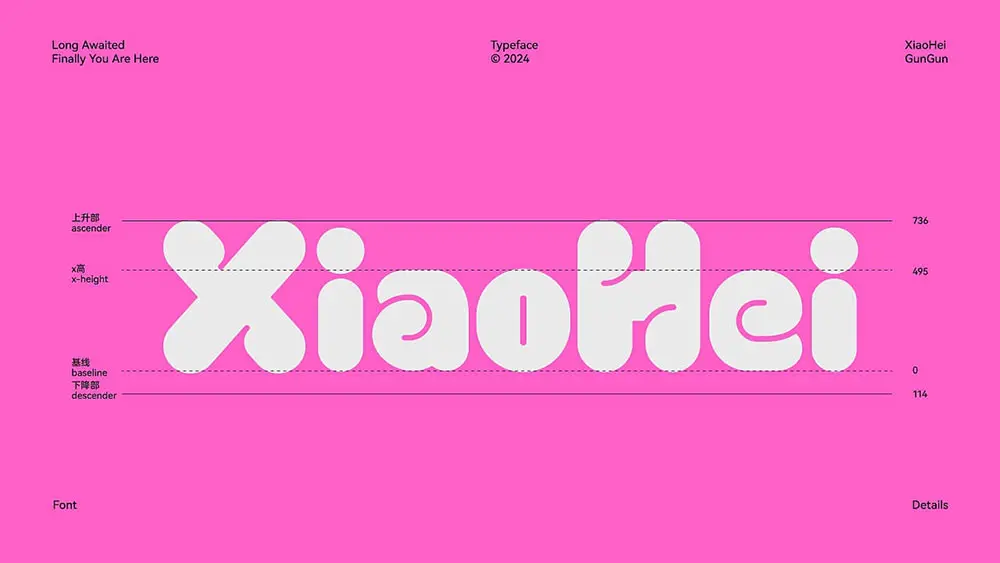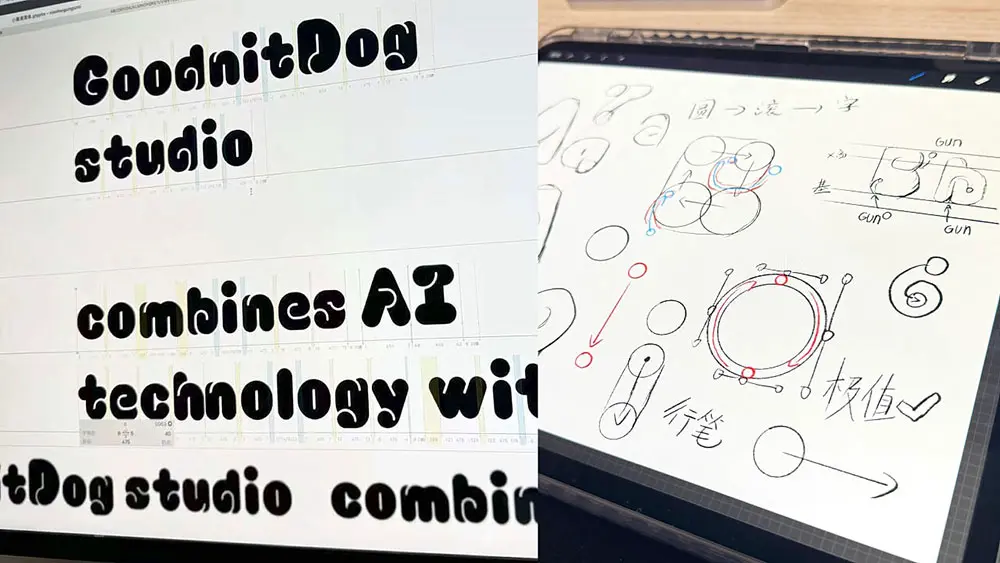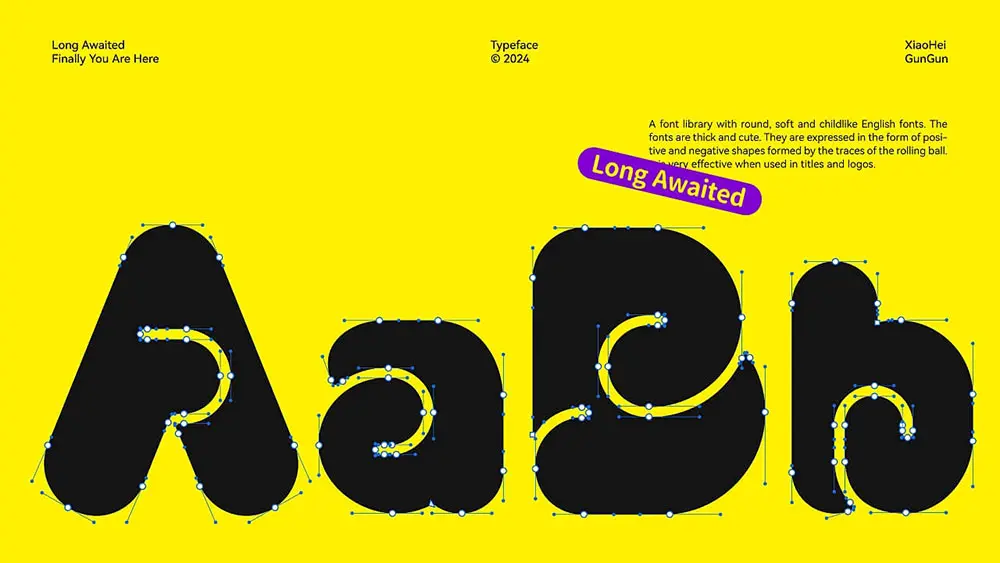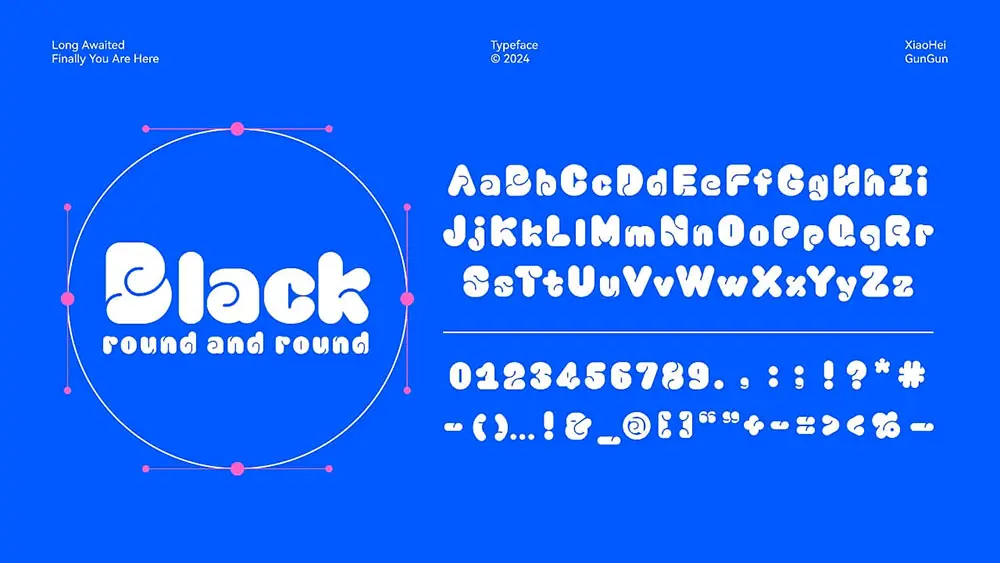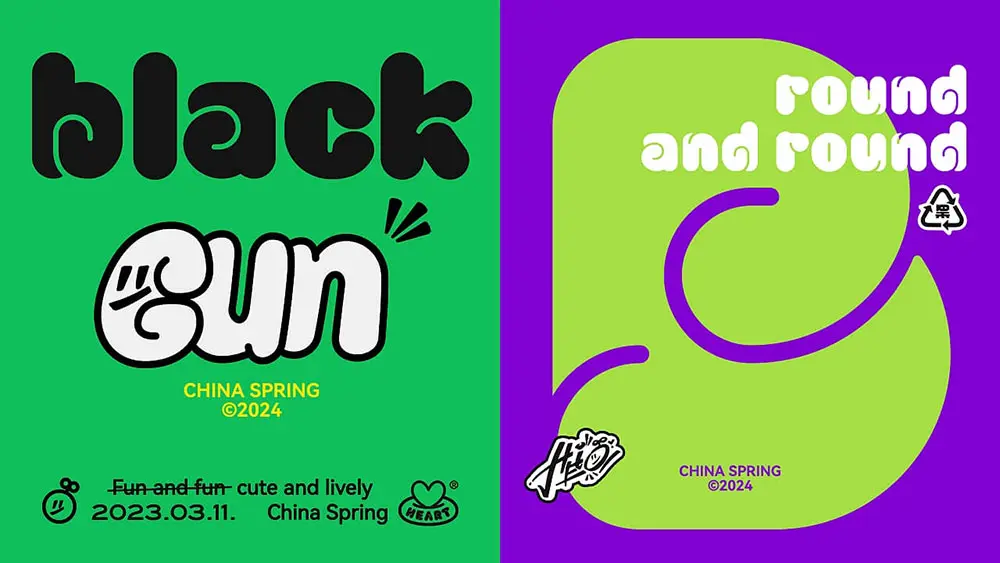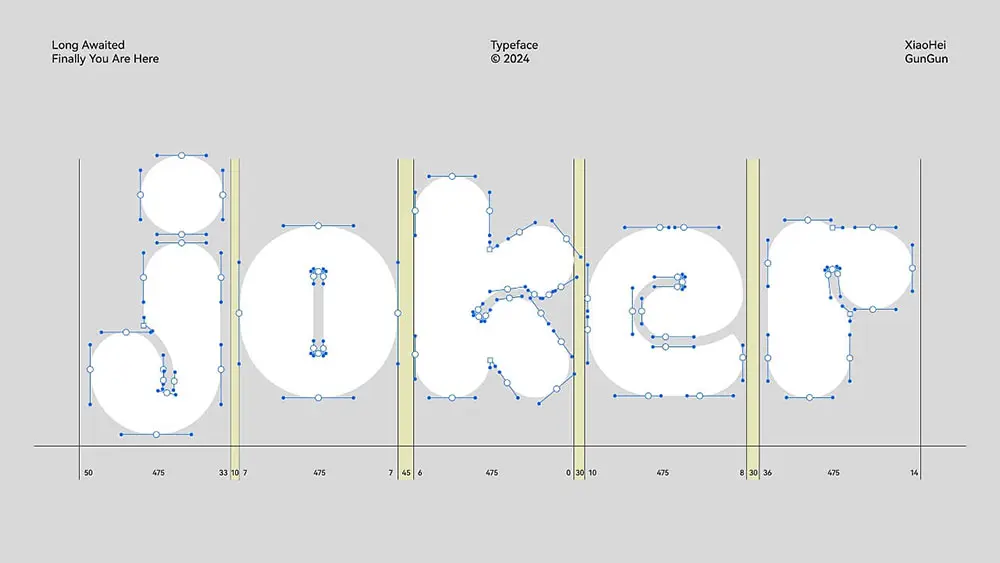
小黑滾滾體預覽
小黑滾滾體介紹
小黑滾滾體 / 英文字庫設計
設計團隊丨GoodnitDog studio 觀念狗
完成日期丨2024年3月
字體設計丨小黑
動效設計丨入墨 / 北也
秉承自由的理念,渾厚可愛,運用圓滾動後的痕跡形成正負形的形式,根據書寫邏輯融合幾何圖形運動去表達,用在標題、logo文字中效果極佳。